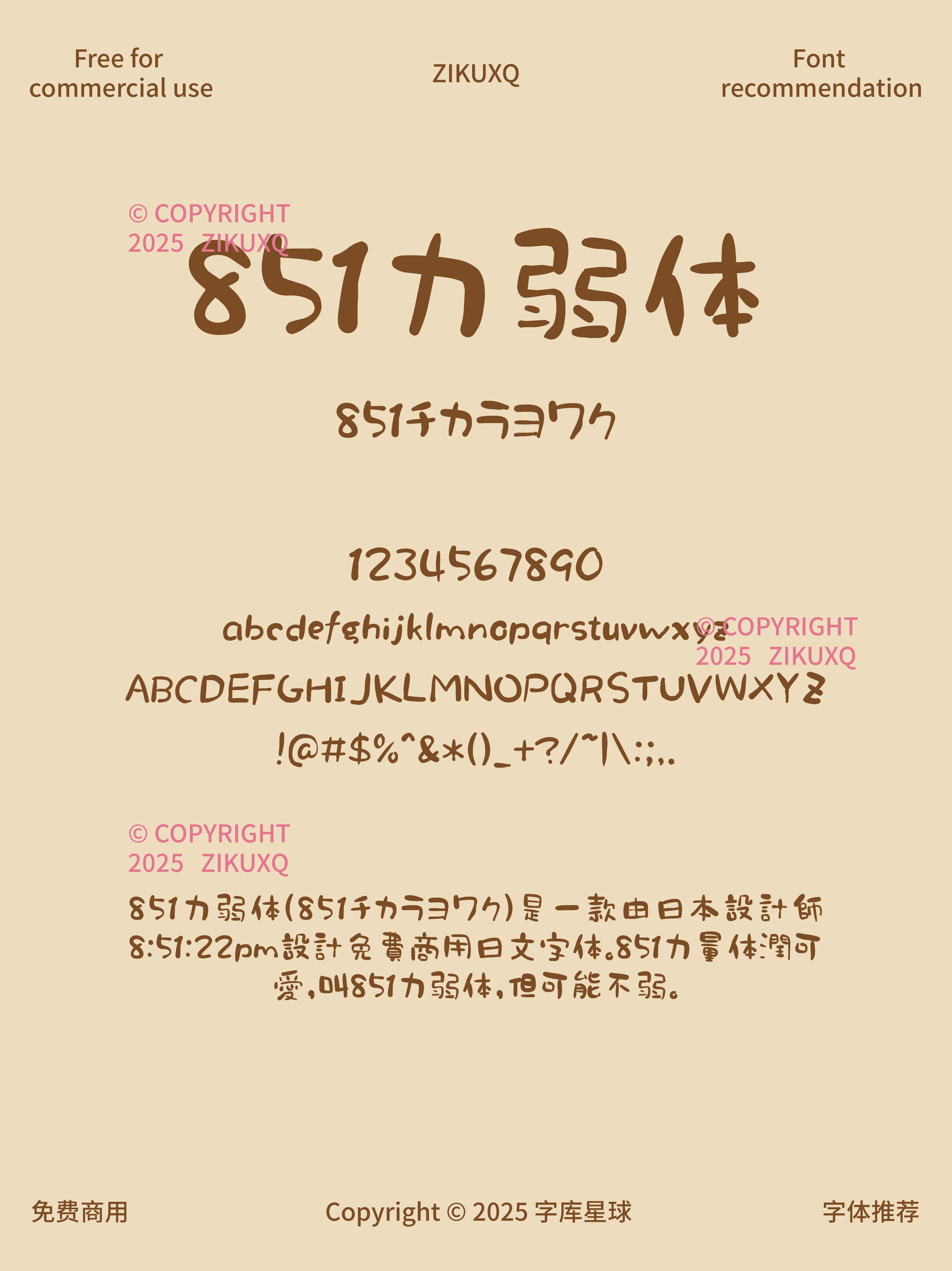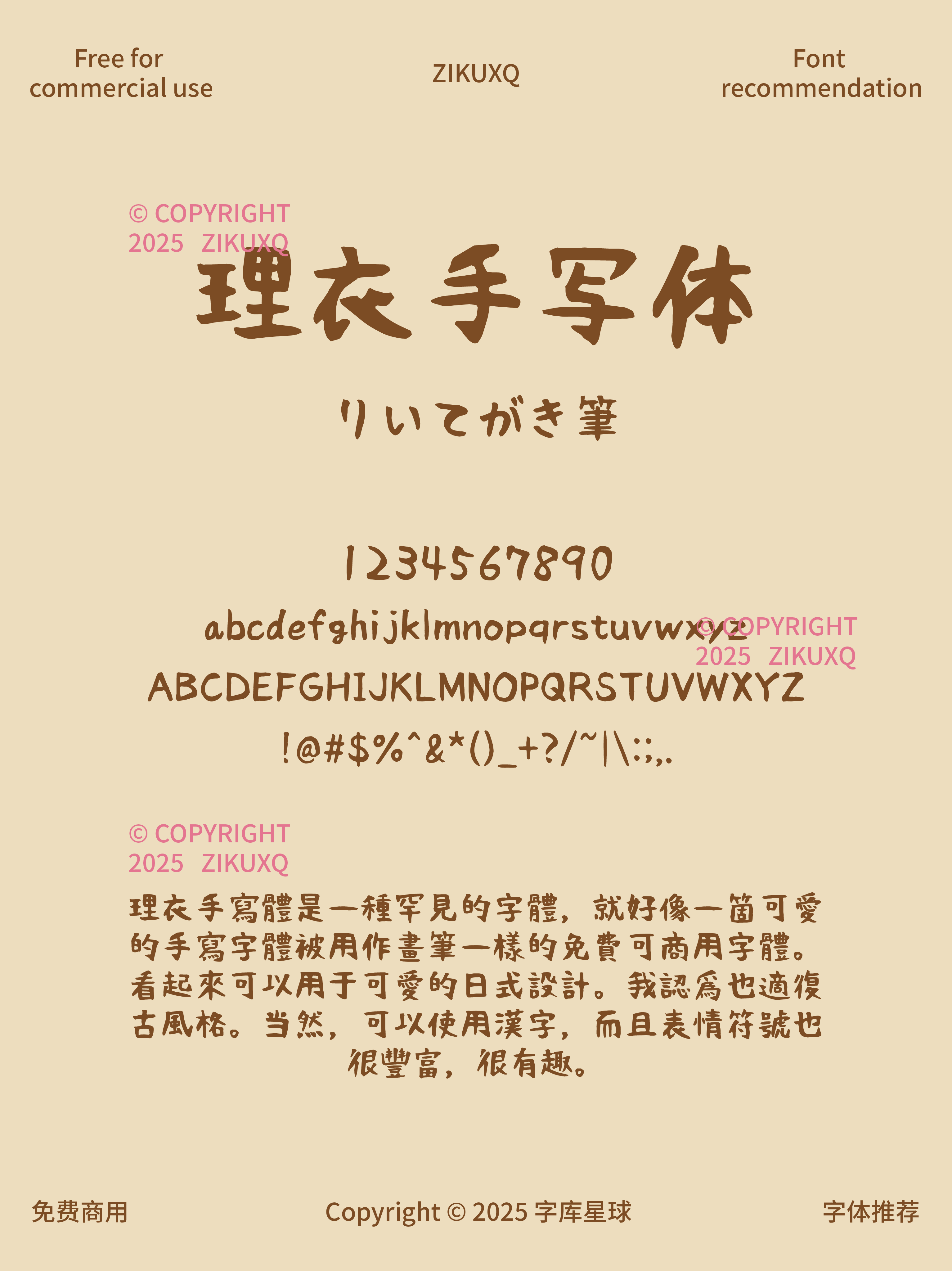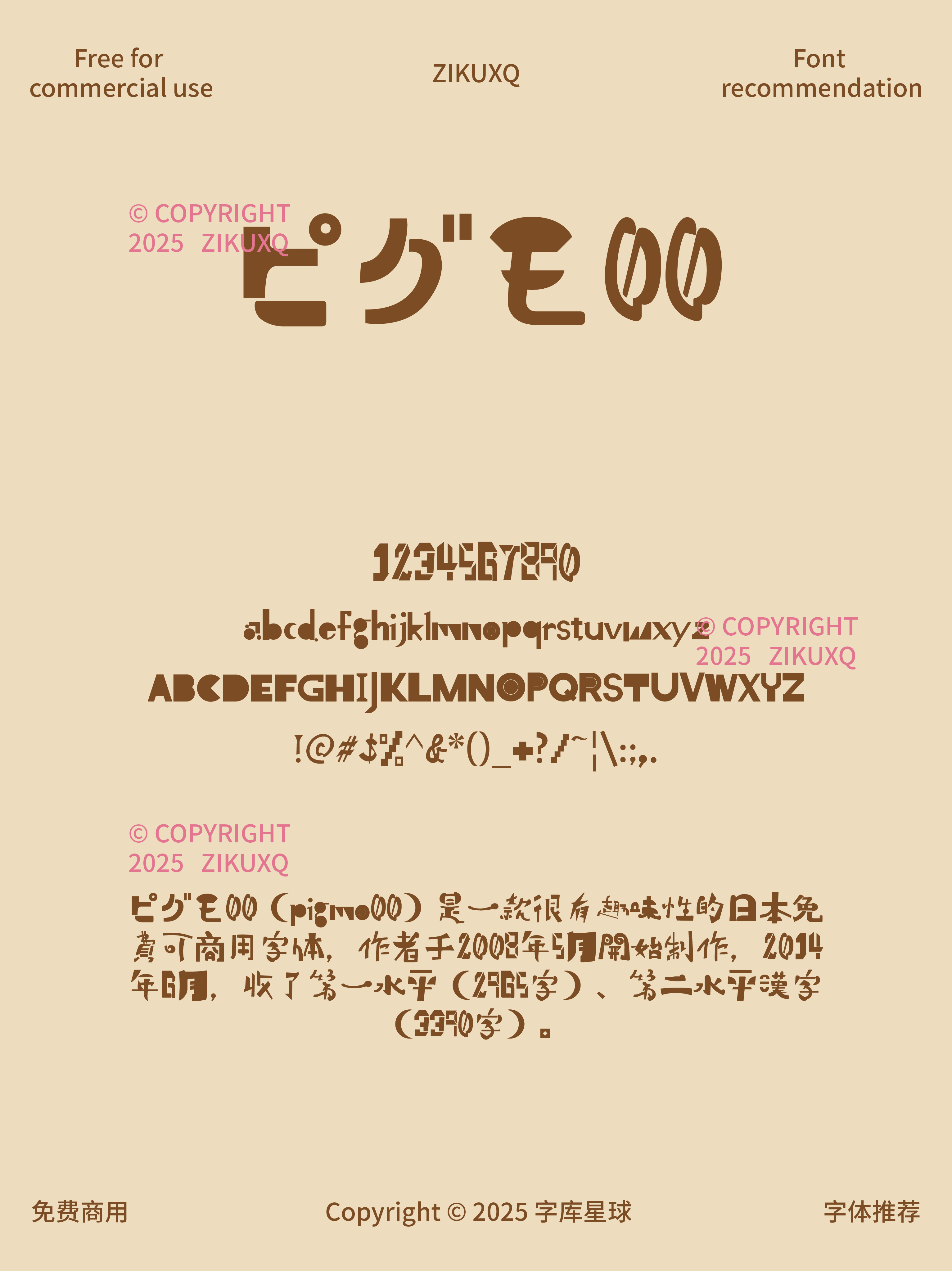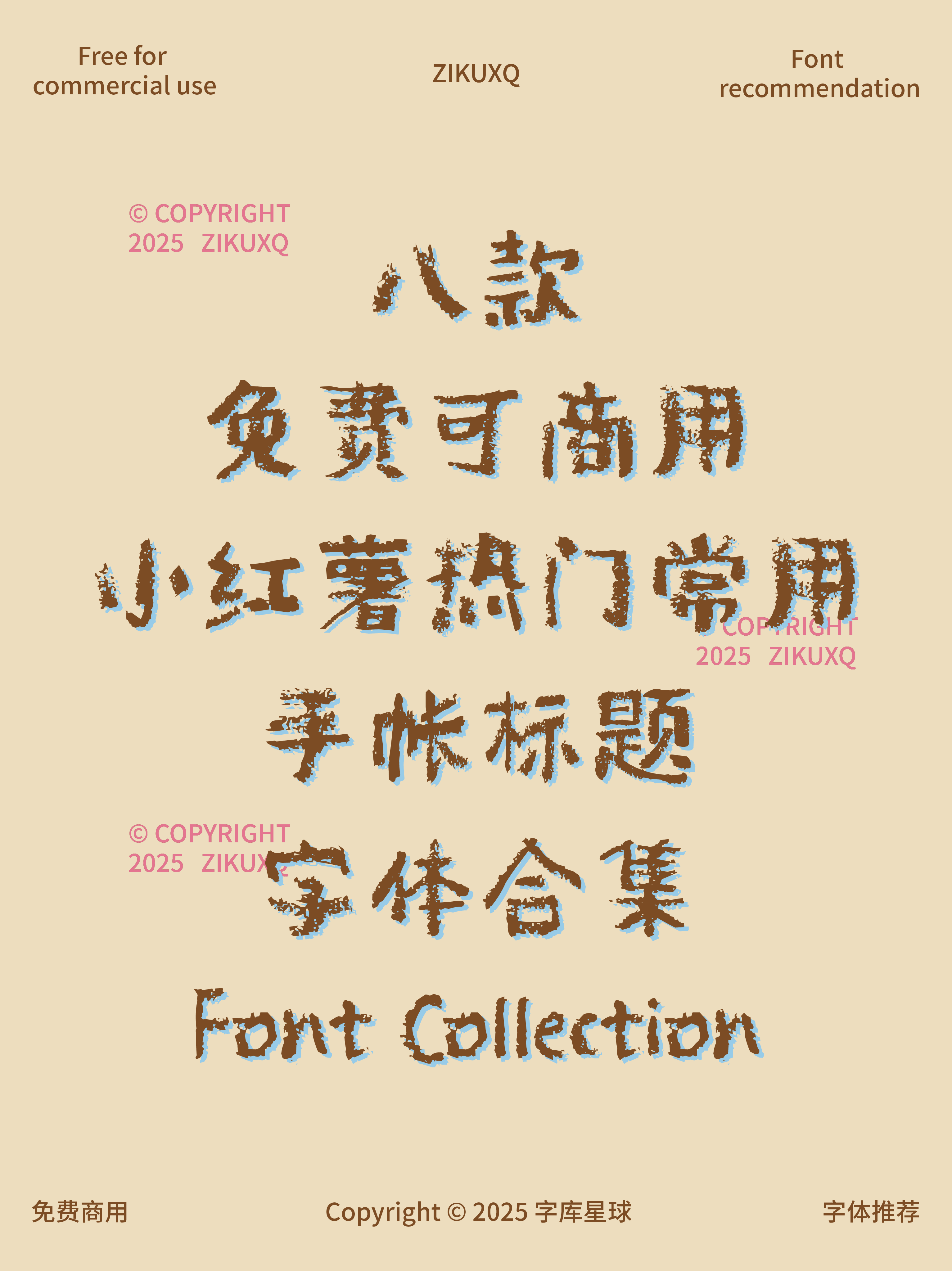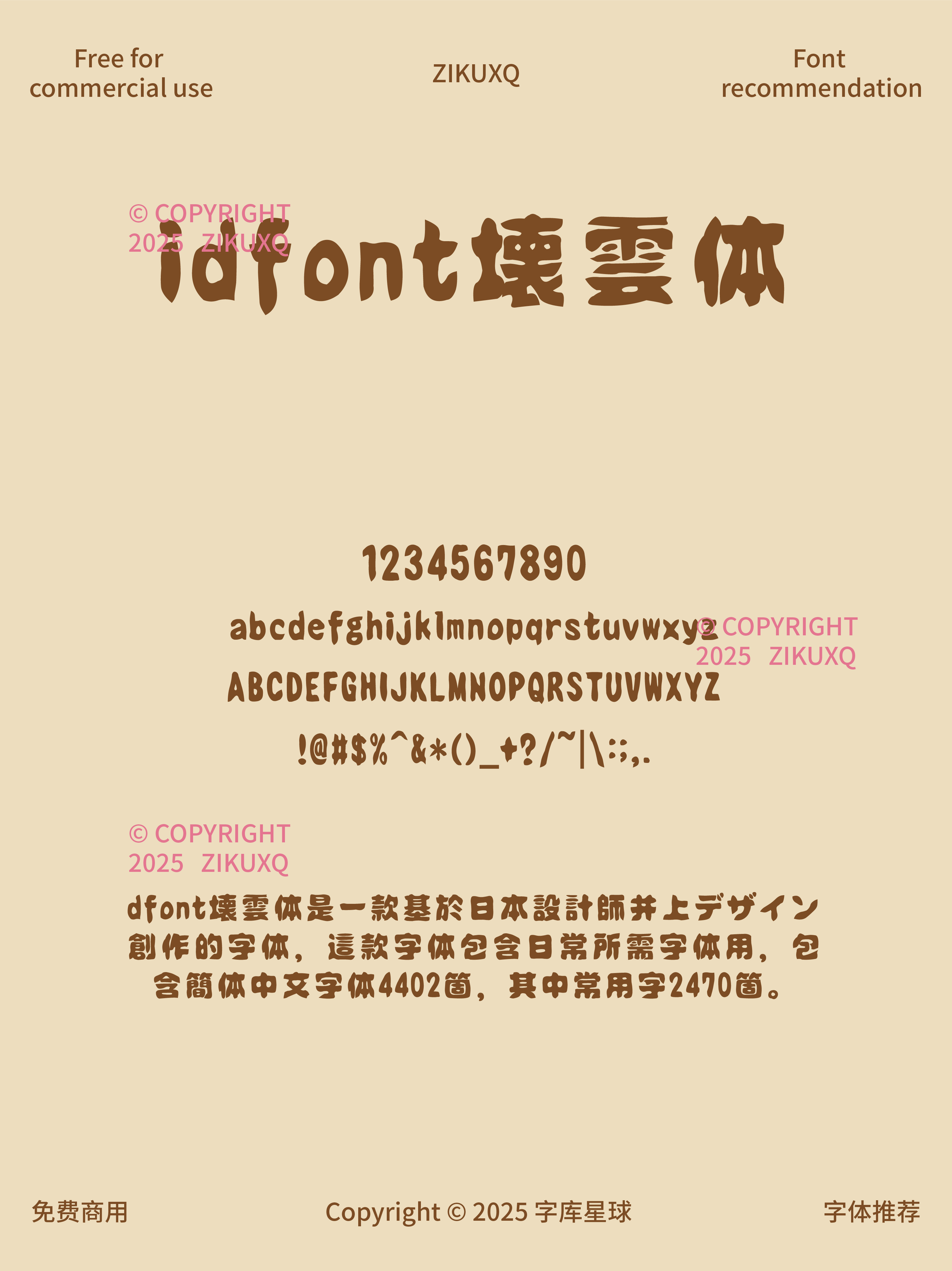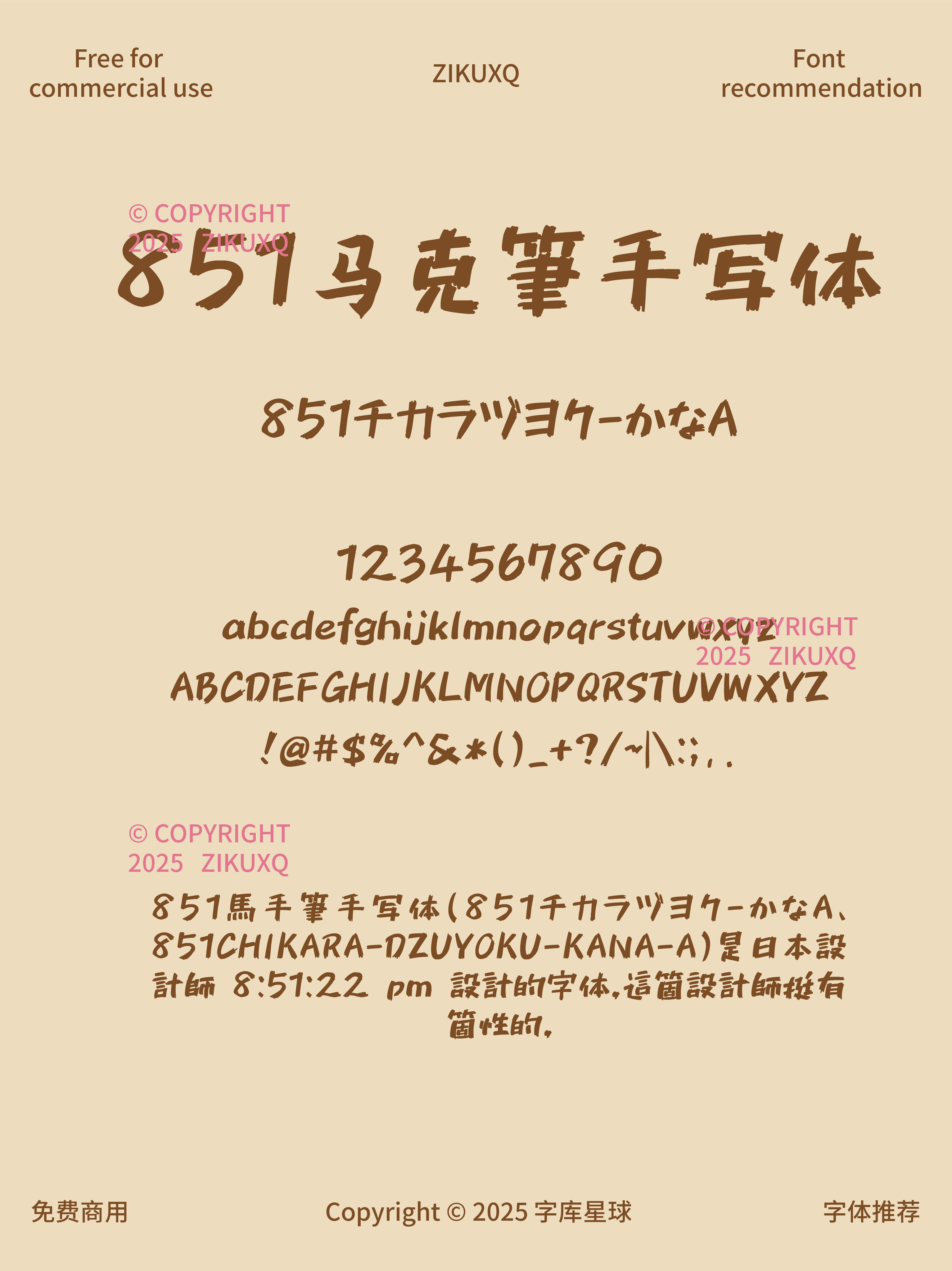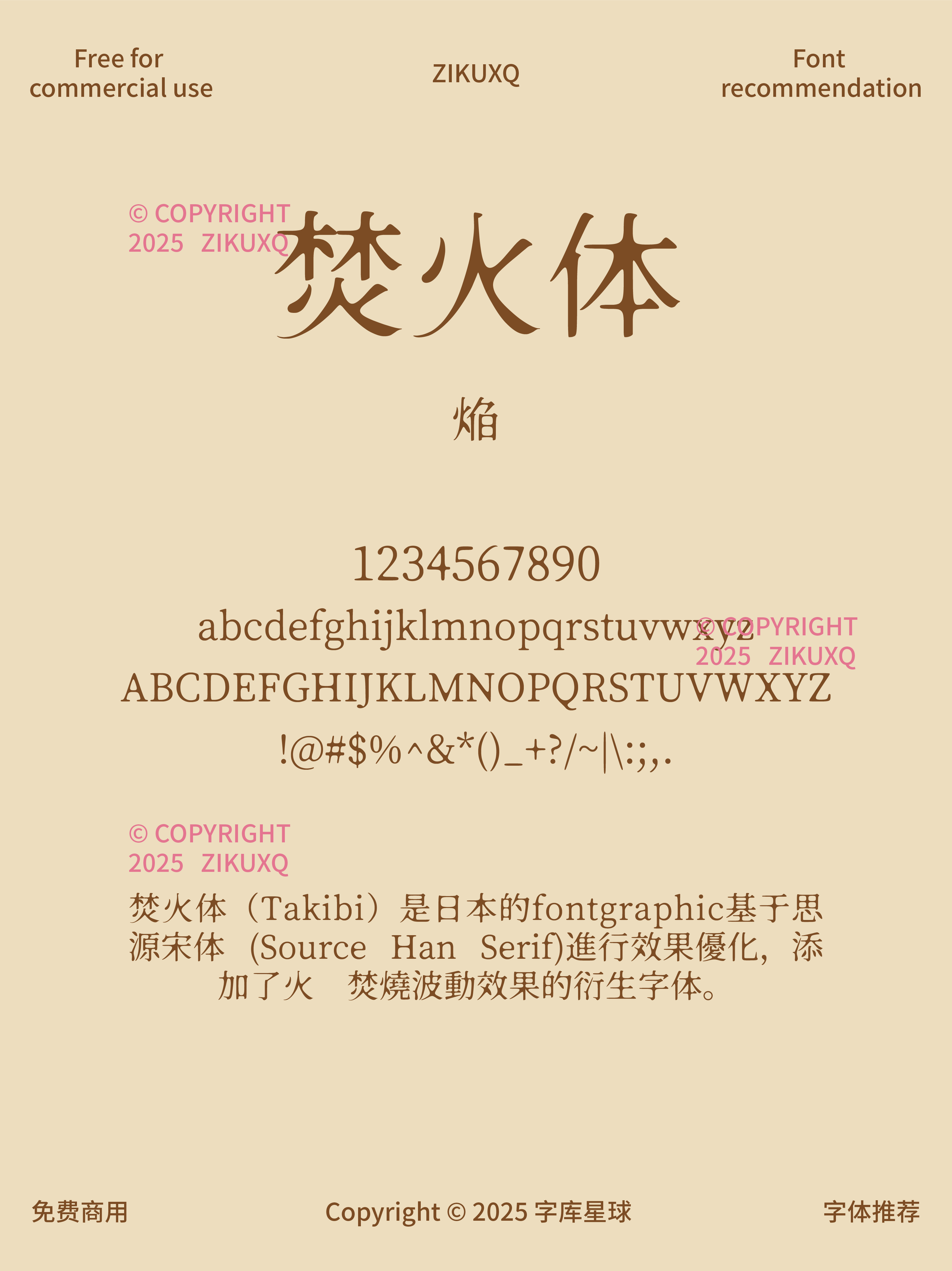
八款免费可商用小红薯热门常用手帐标题字体
做手帐时是不是总为选标题字体发愁?既想要独特吸睛,又担心版权问题。别愁啦,今天就来给大家分享八款超赞的小红书热门手帐标题字体,关键是全部免费可商用哦。
圆滚滚的字体,每个笔画仿佛都由小豆子组成,超级 Q 弹。日系豆豆体非常有治愈感,用于日系风格手帐,比如记录旅行见闻、动漫相关手帐时,能完美营造出那种温馨、可爱的氛围。​